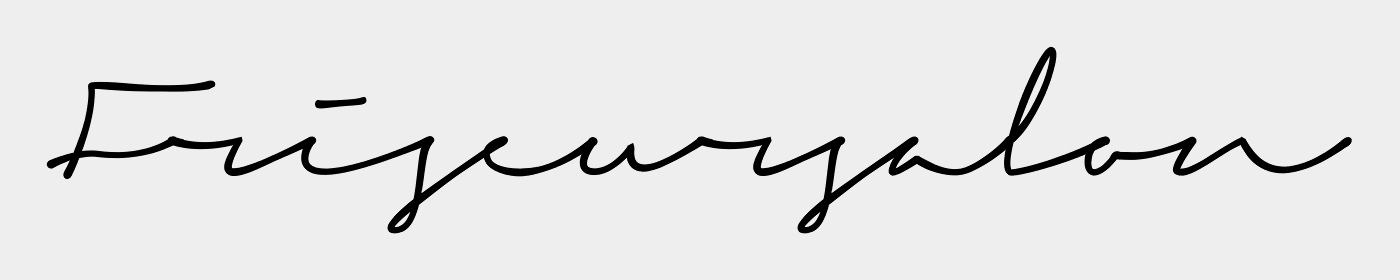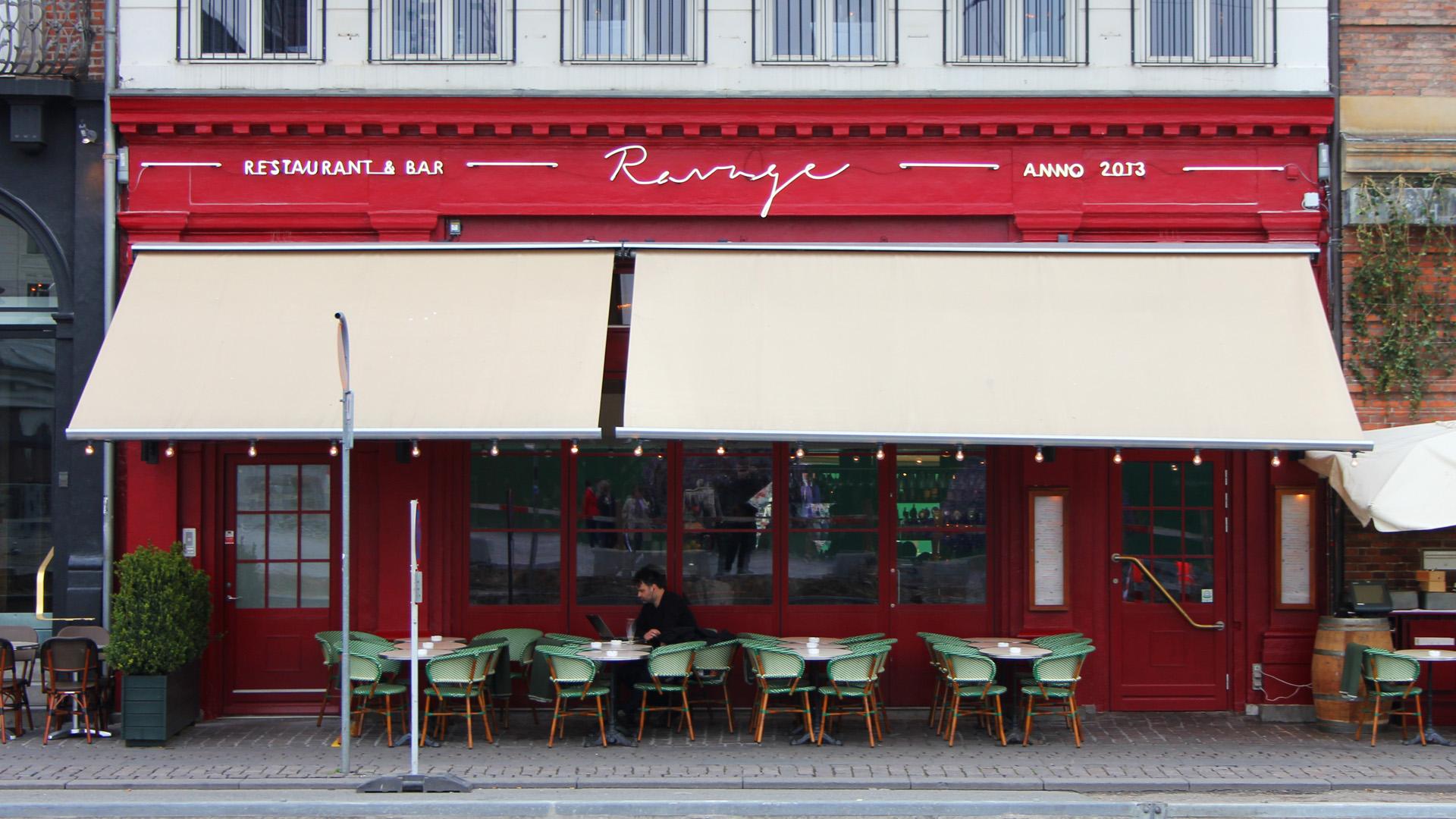
Schreibschrift "50er" Jahre "Leuchtreklame" gesucht
Ich bin auf der Suche nach einer Schriftart, die vornehmlich in den 50er Jahren als Reklameschrift benützt wurde. Heute würde man das wohl salopp "Vintage" nennen.
Hier 2 Beispielbilder, die wahrscheinlich nicht die selbe Schriftart zeigen, dennoch hoffe ich, dass Ihr mir bei meiner Suche behilflich sein könnt.
Wenn ich nun diese Schriftart als Überschrift nehmen würde, welche weitere Schriftart würde sich hierzu dann als Fliesstext anbieten. Hier wäre ich Euch für Euer Feedback und Eure Expertise dankbar.
Das sind alles keine benannten Schriften, sondern beim Schildermaler oder beim Hersteller von Leuchtreklame-Neonröhren, die von Hand gebogen wurden, einfach als "Schreibschrift" bestellt. die genaue Ausgestaltung oblag dann dem jeweiligen Handwerker, und den Möglichkeiten, die das jeweilige Material vorgab, bei Leuchtreklame eben der Möglichkeit die Glasröhren entsprechend zu biegen. Bei der Gaststätten-Leuchtschrift, die ja deutlich neueren Datums ist, ist das wahrscheinlich der vom Betreiber handgeschriebene Schriftzug, der zum Lokalnamen gebogen wurde.